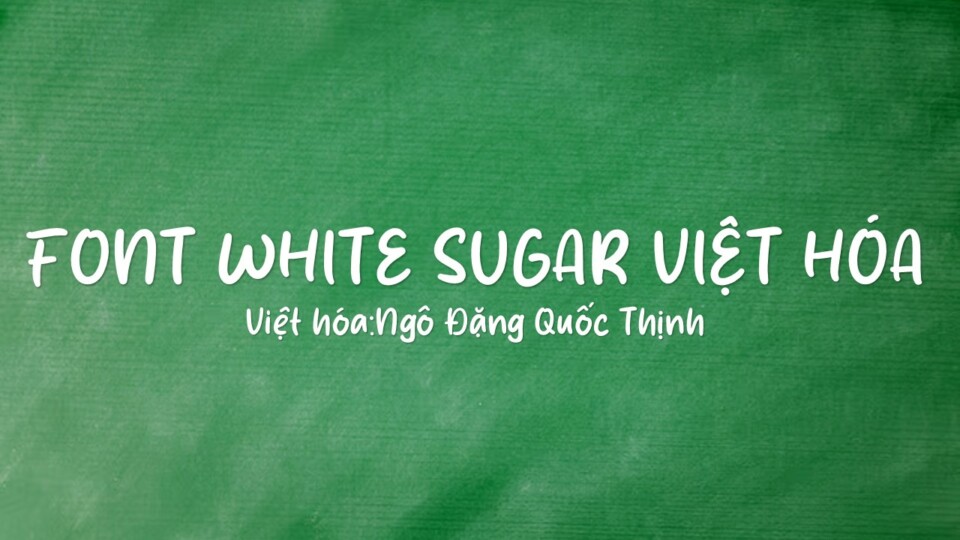
Trong thế giới đồ họa hiện đại, việc lựa chọn Font Chữ phù hợp đóng vai trò then chốt giúp truyền tải thông điệp một cách ấn tượng. Font việt hóa White Sugar nổi lên như một lựa chọn hoàn hảo cho những ai yêu thích phong cách ngọt ngào và trẻ trung. Đây là một phông chữ script mang hơi hướng thủ công, với những đường nét uốn lượn mềm mại tựa như những hạt đường tinh khôi, giúp các bản thiết kế trở nên gần gũi và đầy sức sống hơn bao giờ hết.
Ưu điểm nổi bật của Font việt hóa White Sugar
Phong cách thiết kế độc đáo và hiện đại
Font việt hóa White Sugar sở hữu cấu trúc chữ cái thanh mảnh nhưng vẫn đảm bảo độ dày vừa phải, tạo cảm giác cân đối khi trình bày. Điểm đặc biệt của bộ font này chính là sự kết hợp giữa nét viết tay tự nhiên và sự chỉn chu trong từng ký tự. Điều này giúp các bạn học sinh, sinh viên dễ dàng ứng dụng vào việc làm thiệp chúc mừng, thiết kế bìa sổ tay hay các dự án trang trí trường học một cách linh hoạt.
Khả năng tương thích tốt và hỗ trợ tiếng Việt hoàn chỉnh
Một trong những lý do khiến Font việt hóa White Sugar được ưa chuộng chính là việc đã được tối ưu hóa đầy đủ các dấu câu trong tiếng Việt. Người dùng không còn lo lắng về lỗi font khi gõ các ký tự có dấu phức tạp. Phông chữ này hoạt động mượt mà trên nhiều phần mềm thiết kế phổ biến như Photoshop, Canva hay các ứng dụng văn phòng cơ bản, giúp quá trình sáng tạo nội dung trở nên thuận tiện và chuyên nghiệp hơn.
Ứng dụng thực tiễn và cách sử dụng hiệu quả
Với vẻ ngoài tinh tế, Font việt hóa White Sugar thường xuyên được sử dụng trong các ấn phẩm truyền thông mạng xã hội, thiết kế logo thương hiệu bánh ngọt hoặc trang trí tiêu đề bài giảng. Để đạt hiệu quả thẩm mỹ cao nhất, bạn nên kết hợp phông chữ này với các tông màu pastel nhẹ nhàng. Hãy nhanh tay tải về để trải nghiệm sự khác biệt từ Font Miễn Phí, Font Việt Hóa, Font việt hóa White Sugar ngay hôm nay.